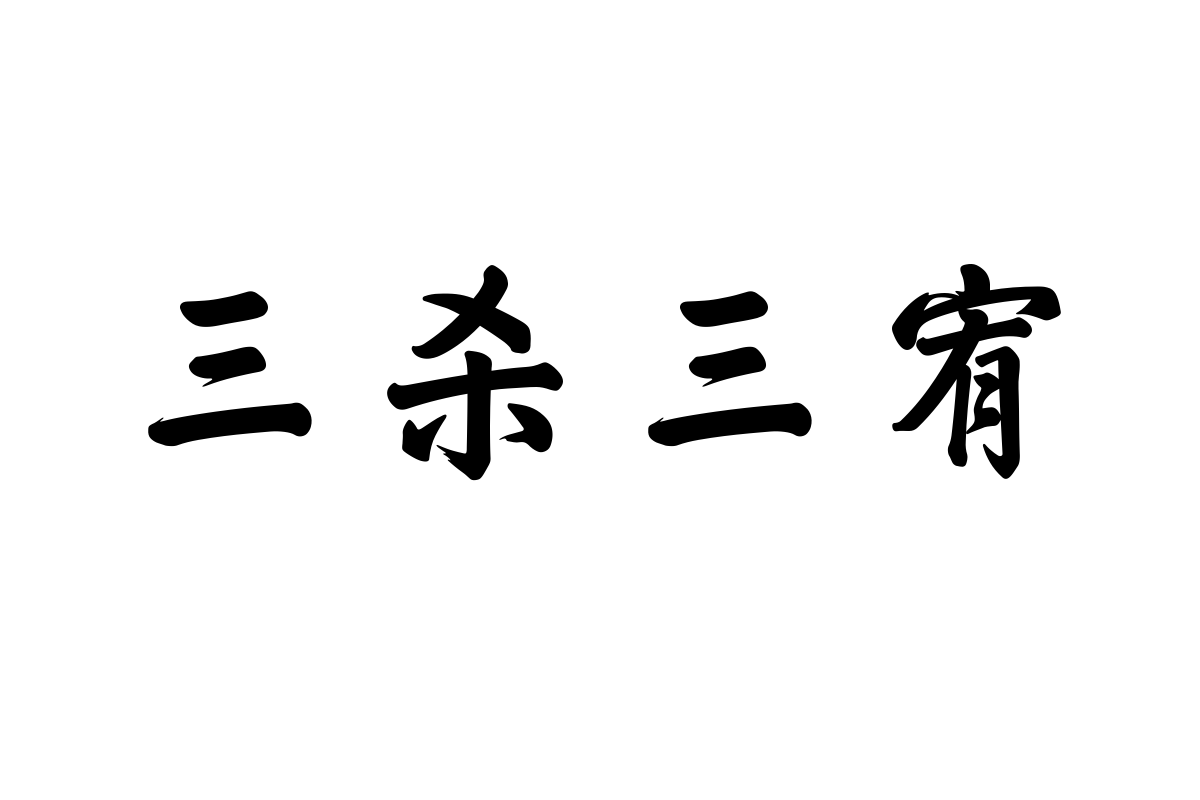
汉仪颐和仙境W是一款具有独特艺术风格的中文字体,由汉仪字库出品。这款字体以其独特的设计、优雅的线条和流畅的笔画而闻名,给人以宁静、和谐的感觉。
字体特点:
1. 字形独特:汉仪颐和仙境W采用独特的艺术风格,字形结构独特,线条流畅,给人以视觉上的享受。
2. 优雅美观:字体线条流畅,笔画优美,整体给人一种优雅、高雅的感觉,适合用于需要表现高贵、典雅氛围的场合。
3. 适用广泛:适用于各种印刷品、广告、设计等领域,如书籍、杂志、报纸、海报等。
字体风格:
汉仪颐和仙境W是一款具有艺术感的中文字体,其设计风格独特,线条流畅,给人以宁静、和谐的感觉。这款字体适合用于需要表现高贵、典雅氛围的场合,如广告、设计等领域。